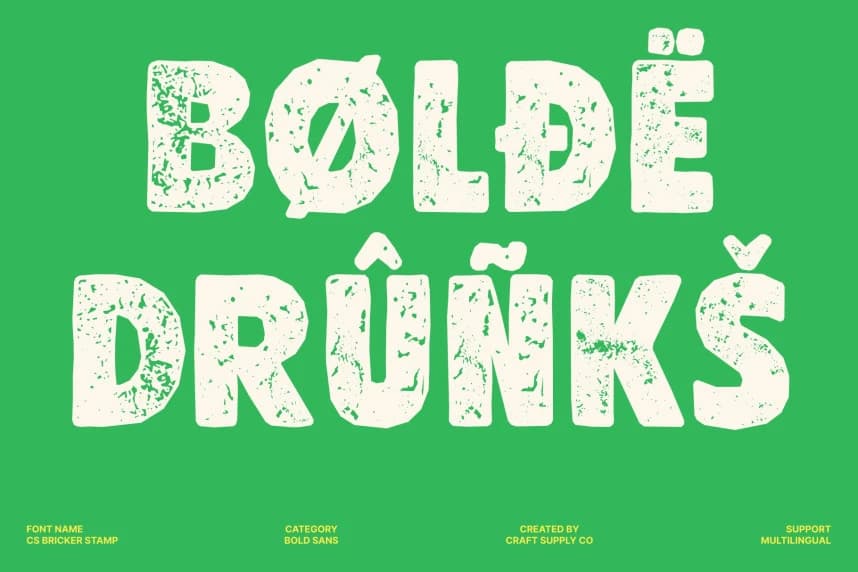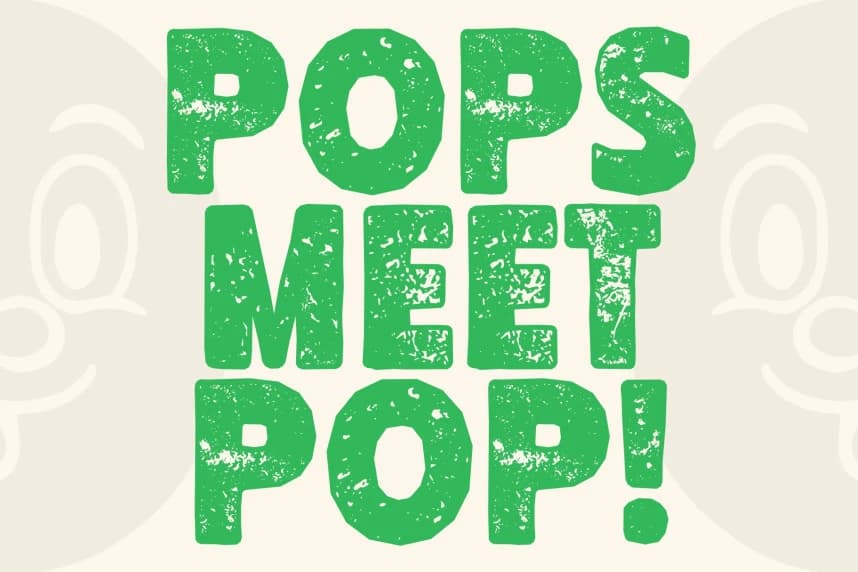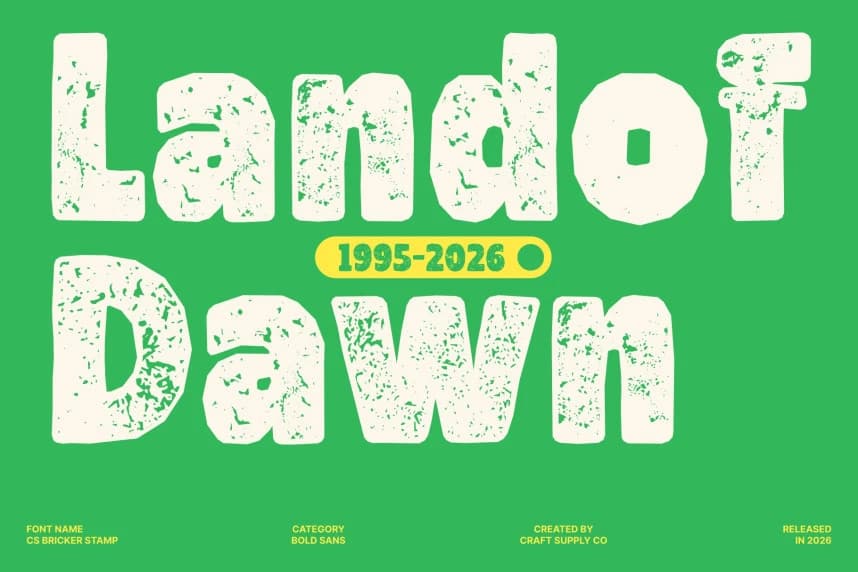
CS Bricker Stamp Font
CS Bricker Stamp Font – Dokulu Y2K Enerjisiyle Fütüristik Kalın Yazı Tipi; Y2K Karakterli Kalın Sans-Serif. Bu, belirgin damgalı dokuyla birlikte kalın, çılgın ve fütüristik formları bir araya getiren modern bir sans-serif yazı tipidir.
CS Bricker Stamp Font – Y2K Enerjisiyle Dokulu Gelecek Odaklı Kalın Yazı Tipi. Y2K Karakterli Kalın Sans-Serif. Bu, belirgin damgalı dokuyla kalın, garip ve fütüristik formları birleştiren modern bir sans-serif yazı tipidir.
CS Bricker Stamp